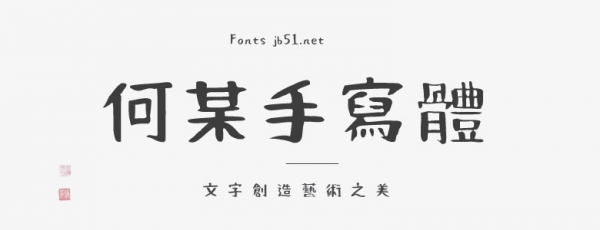
何某手寫體(NaniFont、何某手寫)是Max基于日本的おつとめフォント字體(源字體遵循SIL開源字體協(xié)議)增補(bǔ)修改而成的一款自由手寫體。與原作者的主要差異是調(diào)整部件寫法、新增中文字、增加一些符號,值得一提的是增加4個字重,現(xiàn)一共擁有5個字重。經(jīng)過Max的增補(bǔ),何某手寫體對簡體的字體支持也挺不錯的。
對現(xiàn)代人來說,毛筆字體不是可讀性好的字體。但是手寫文字和勘亭流等優(yōu)秀的文字經(jīng)常被用于促銷用的傳單和海報(bào)等。因此,何某手寫體是根據(jù)毛筆文字的使用實(shí)際情況,重視“可視性高”為目標(biāo)而制作的字體,大家不妨一試!